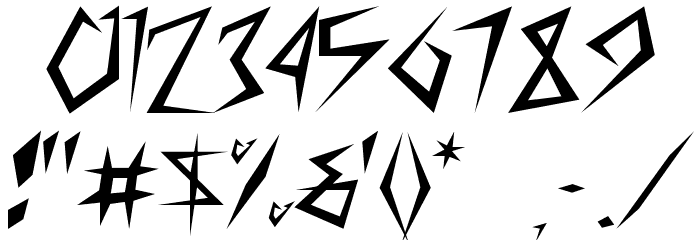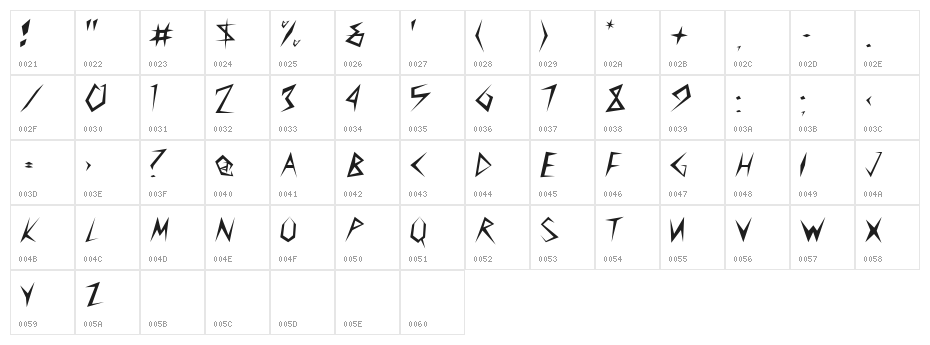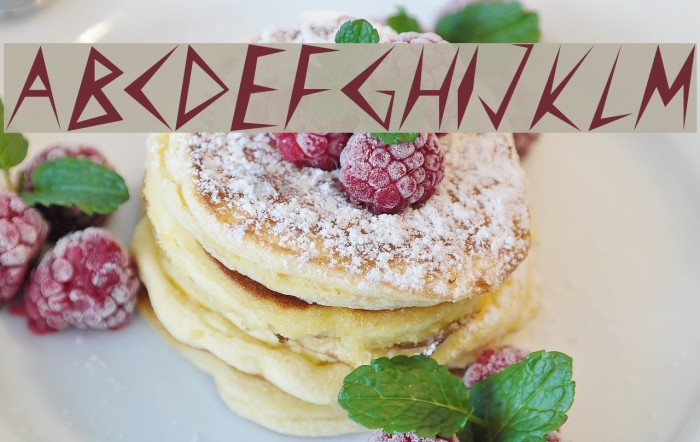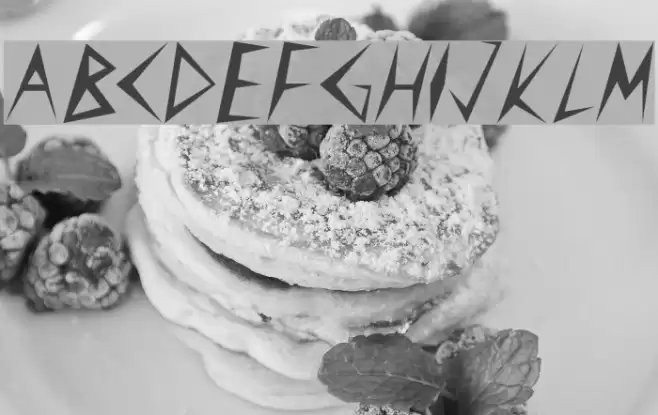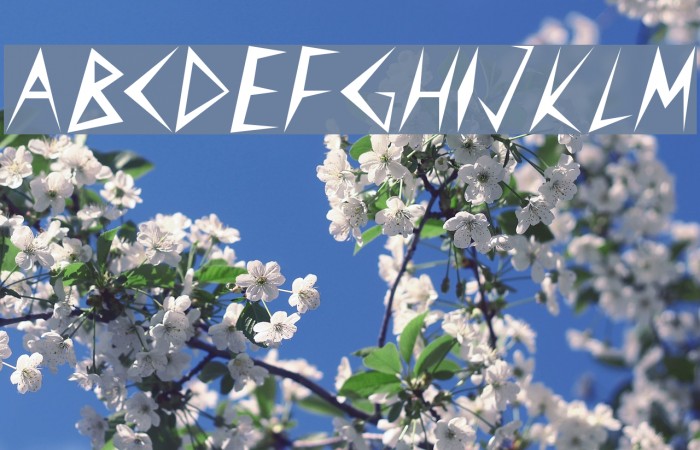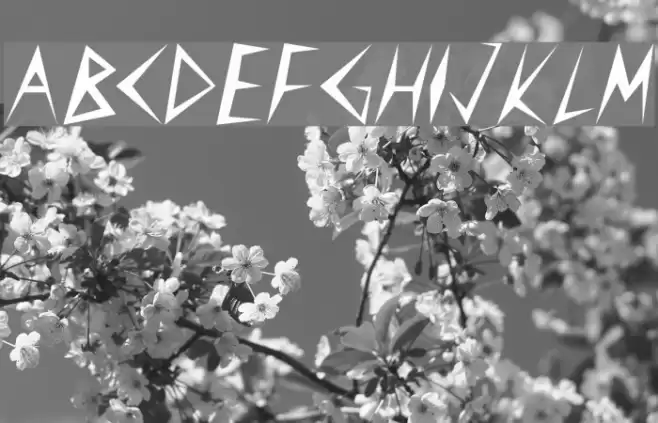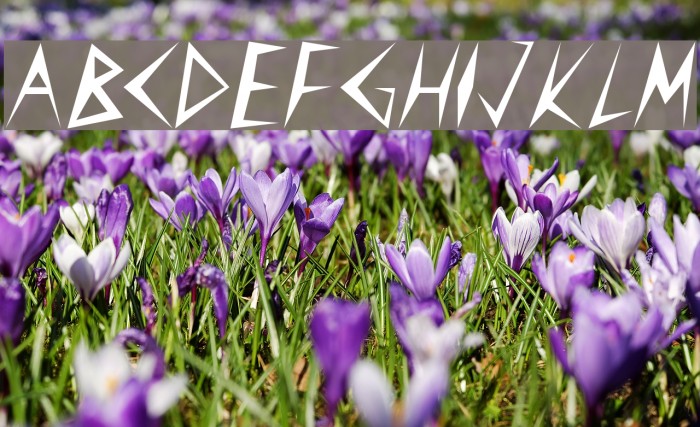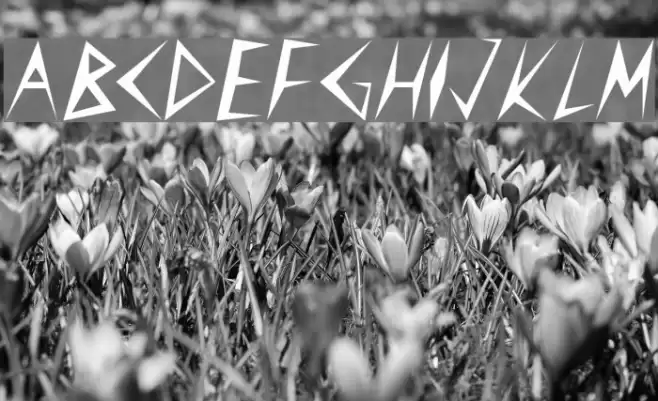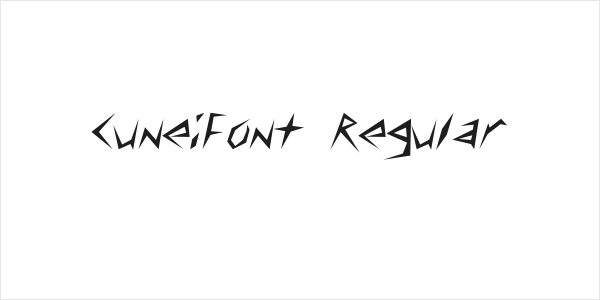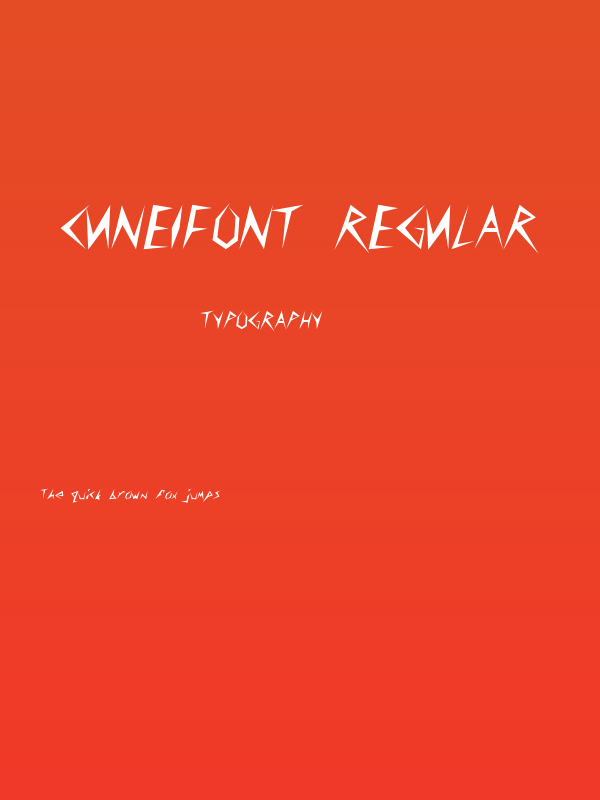
CuneiFont Regular Font
| Style général | Modern, Futuristic, Edgy |
| Projets proposés | Ideal for use in video game titles, sci-fi movie posters, edgy branding, and modern art projects. |